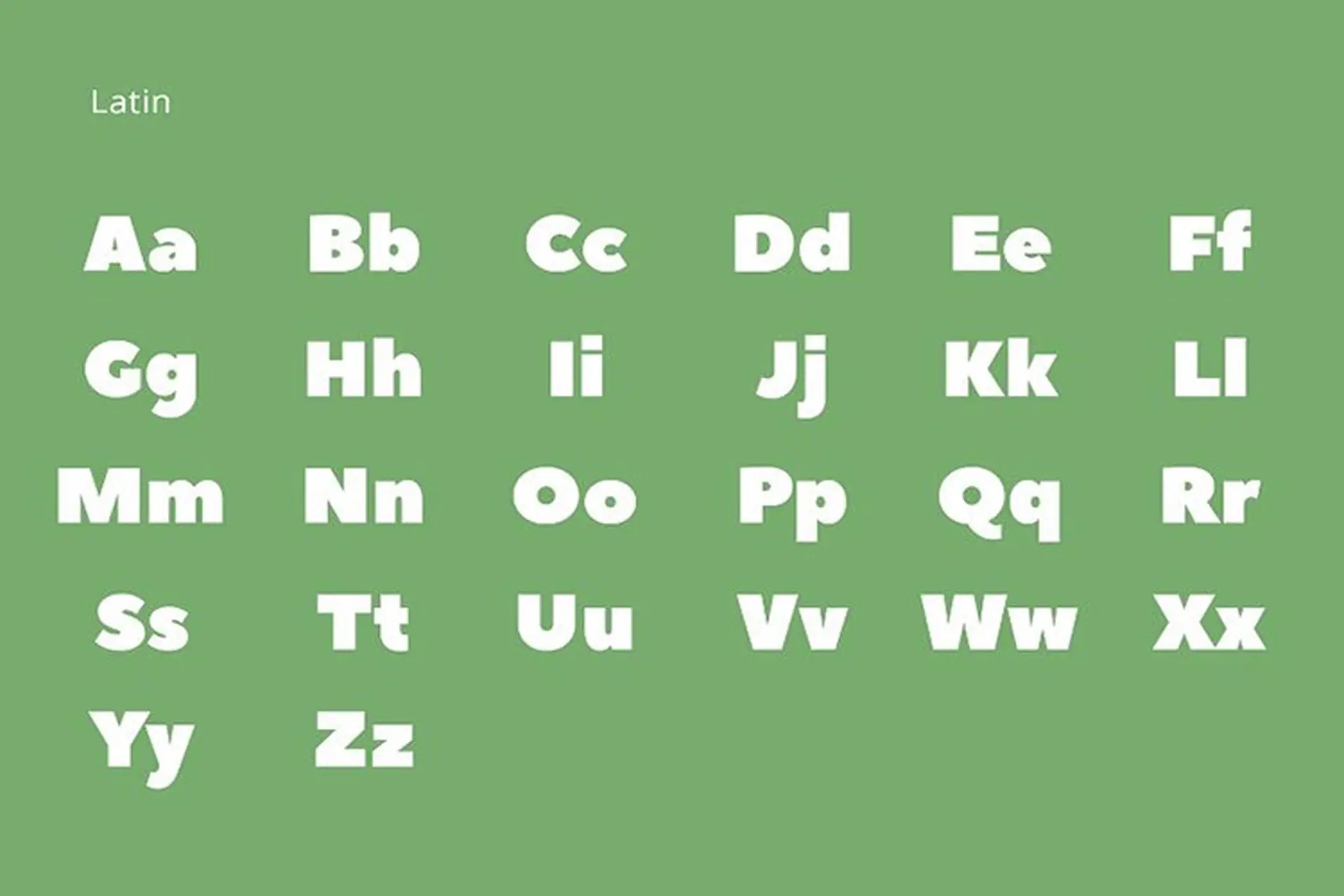
Font chữ không chân viết tay (sans-serif font) là font không có chân chữ, nét đơn giản được sử dụng rộng rãi trong thiết kế bao bì hiện đại, túi giấy minimalist và in ấn cho thương hiệu contemporary.
Font không chân với đặc điểm sạch sẽ, dễ đọc tạo cảm giác hiện đại, chuyên nghiệp. Ở bài viết này, In Viva hướng dẫn tải font chữ không chân với hơn 20 mẫu miễn phí, phù hợp cho mọi nhu cầu thiết kế và in ấn.
Font chữ không chân (sans-serif) là gì?
Font chữ không chân (sans-serif) là font không có chân chữ (serif) ở đầu và cuối nét. “Sans” trong tiếng Pháp có nghĩa là “không có” – sans-serif = không có chân.
Sans-serif ra đời muộn hơn serif (thế kỷ 19 vs thế kỷ 15), ban đầu bị coi là “grotesque” – kỳ dị vì thiếu chân chữ. Nhưng đến thế kỷ 20, với phong trào modernism, sans-serif trở thành biểu tượng của thiết kế hiện đại.
Phân loại font sans-serif:
- Grotesque (neo-grotesque): Sans-serif cổ điển, trung tính. Ví dụ: Helvetica, Arial. Cảm giác: chuyên nghiệp, trung tính, corporate.
- Geometric: Dựa trên hình học (tròn, vuông). Ví dụ: Futura, Gotham. Cảm giác: hiện đại, sạch sẽ, minimalist.
- Humanist: Sans-serif với nét ấm áp, organic. Ví dụ: Gill Sans, Frutiger. Cảm giác: thân thiện, dễ tiếp cận, human.
Ưu điểm font không chân:
- Hiện đại, clean: Sans-serif là font của thế kỷ 20-21, tạo cảm giác contemporary, forward-thinking.
- Dễ đọc trên màn hình: Không có chân nên pixel rõ ràng hơn ở độ phân giải thấp – lý do website, app đều dùng sans.
- Versatile – đa năng: Sans-serif phù hợp từ body text, tiêu đề đến logo, signage.
- Minimalist, không rườm rà: Nét đơn giản tạo cảm giác tinh gọn, không cầu kỳ.
Bảng tổng hợp font sans-serif phổ biến như sau:
Tên font |
Loại sans-serif |
Ứng dụng in ấn tốt nhất |
Inter |
Neo-grotesque, screen-optimized | Bao bì tech, UI/UX, digital product |
Lato |
Humanist, ấm áp | Bao bì thực phẩm, cafe, wellness |
Poppins |
Geometric, versatile | Bao bì startup, túi giấy thời trang trẻ |
Montserrat |
Geometric, urban | Logo thời trang, poster sự kiện |
Roboto |
Neo-grotesque, Android | Bao bì điện tử, app, software |
Open Sans |
Humanist, friendly | Brochure, catalogue, body text |
Nunito |
Rounded humanist | Bao bì kids, organic, friendly brand |
Raleway |
Geometric elegant | Logo luxury minimalist, catalogue |
Work Sans |
Grotesque, optimized screen | Website, app, bao bì digital product |
Oswald |
Condensed, bold | Poster, standee, tiêu đề impactful |
Lưu ý: Font sans-serif thường dễ kết hợp với nhau hơn serif – có thể dùng 2 sans khác nhau trong cùng thiết kế.
Ứng dụng font không chân trong bao bì hiện đại
Font không chân với phong cách hiện đại được ưa chuộng:
- Font của thế kỷ 21: Sans-serif là default của digital age – Google, Apple, Microsoft đều dùng sans cho UI, tạo liên tưởng hiện đại, tech-forward.
- Minimalist, clean: Sans-serif phù hợp xu hướng thiết kế tối giản – less is more, focus vào sản phẩm không phải decoration.
- Versatile nhất: Sans-serif là “jeans” của typography – phù hợp mọi ngành từ tech, food, fashion đến wellness.
- Dễ đọc, accessible: Sans rõ ràng ở mọi kích thước, phù hợp người lớn tuổi, trẻ em, người kém thị lực.
Font không chân xuất hiện trong hầu hết sản phẩm in ấn hiện đại:
- Bao bì công nghệ: smartphone, laptop, gadget, electronics.
- Túi giấy thương hiệu: startup, e-commerce, direct-to-consumer brand.
- Bao bì thực phẩm modern: healthy food, meal prep, protein bar, smoothie.
- Nhãn sản phẩm: barcode, ingredient list, nutritional info – cần font rõ ràng.
- Poster sự kiện: conference, workshop, meetup.
- Name card: business card hiện đại, minimalist.
1. Khi nào nên dùng sans-serif thay vì serif?
Dùng sans-serif khi muốn: hiện đại/tech (startup, app), minimalist/clean (lifestyle brand), casual/friendly (cafe, F&B), easy-to-read (signage, instruction). Dùng serif khi muốn luxury, formal, classic.
Font chữ không chân hiện đại, clean, versatile – phù hợp hầu hết mọi bao bì, in ấn hiện đại. Tải miễn phí từ Google Fonts.